前言:我来了,这是U1系列新开篇章实战篇,不仅仅是适用于UI设计,甚至包含网页设计、平面设计。在文章中会更多的介绍一些操作上的教学,希望对新人们有帮助。
推荐字体
很多小伙伴在做设计的时候,无论是排版还是展示,都不太注重字体,或者有些太过于注重以至于用了很多种字体。实际上,当你做的年头越久,你电脑里的字体往往越少,因为非常有用的字体就那么几种。
这一篇内容就讲的是老牛平时常用的一些字体,可能有些是你想不到的,却又比较合适做设计以及展示。那么电脑里最该保留那几个字体呢?大家继续往下看。
这个字体是老牛最爱用的字体之一,甚至在我的QQ里都设置了这个字体。
并且它还有三种粗细样式,其中包括:
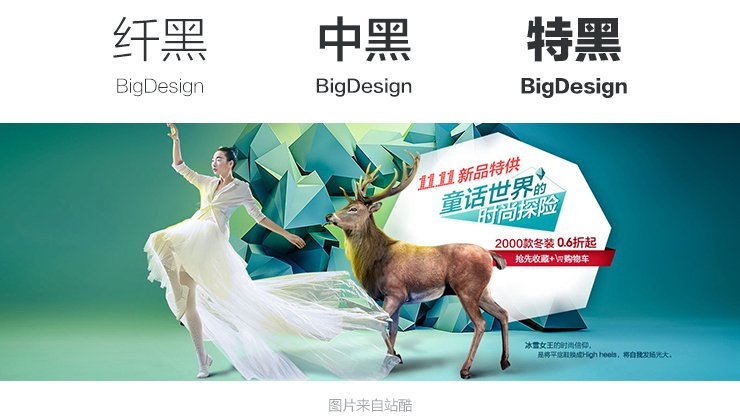
一个banner,一个画册,一个网页,用了一款好的字体都会提升逼格,甚至APP产品本身,如果能够在展示和做设计图的时候采用好的字体,更会为这款产品加分。
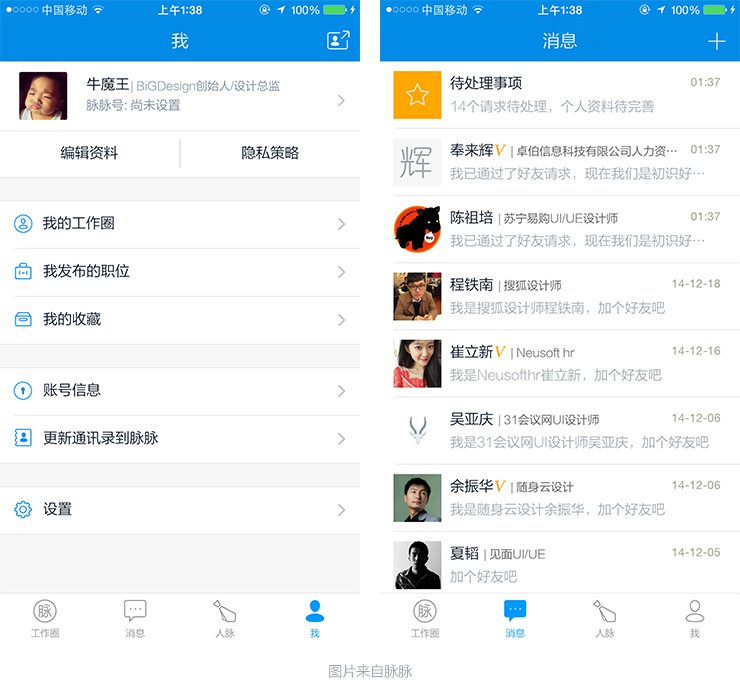
第二款:
这个字体是Adobe与Google宣布推出的一款开源字体,可能不用过多的介绍,相信大部分小伙伴已经下载并且使用了。这款字体更为良心的是,共有七种不同的粗细,无论是做内文还是做标题,绝对足够了。
老牛很喜欢在做PPT以及APP的时候都用到,因为它覆盖率比较广,很多人的电脑都安装并且使用了,其次它七种粗细的天然优势完虐各种PPT文案。
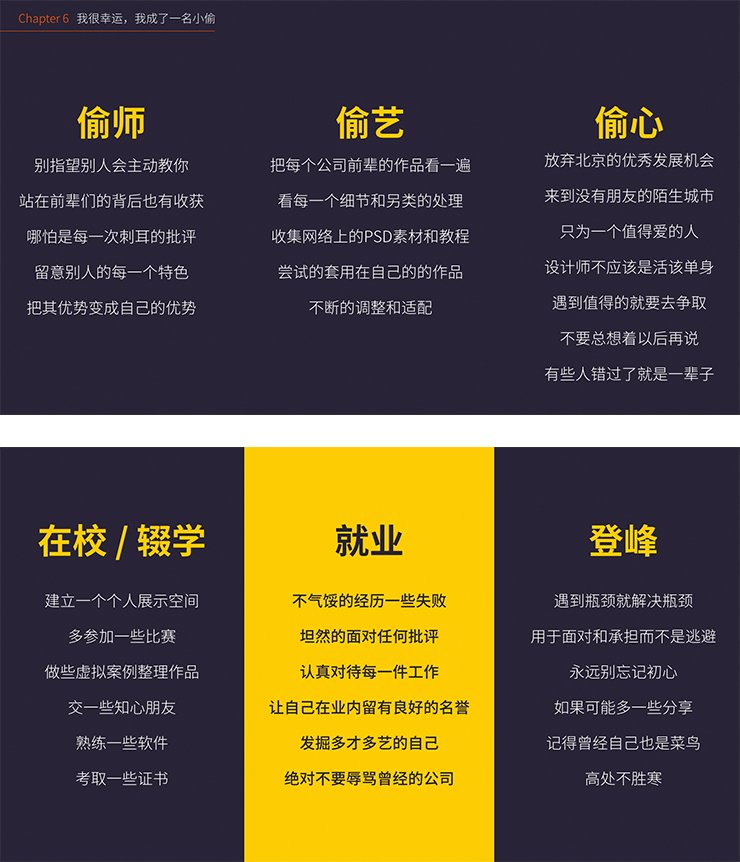
曾经最多使用的是微软雅黑,也是因为其覆盖面比较广,现在有了思源就更多了一种选择。APP的闪屏以及一些Layout图,使用的频率最高。
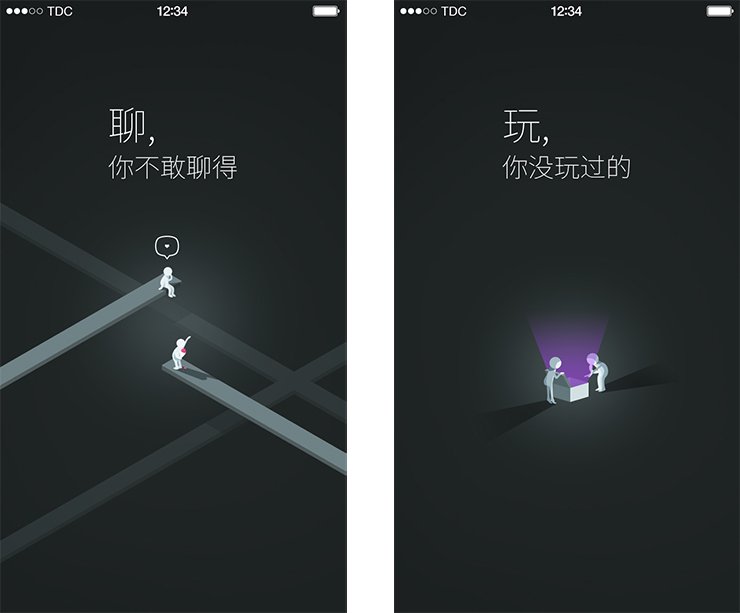
第三款:
这个字体可能每个人的电脑都有(默认字体?),但是使用的人不是很多吧!之前老牛做过的一些设计展示图被很多人问到的字体,就是这个。好吧你让我打出来名字我还真是打不出来的……
它的粗细样式也比较多,共有六种,更主要的是,个人认为它的英文字母会较兰亭和思源更漂亮一些,所以当做中英文结合的时候我就常常使用这套字体。
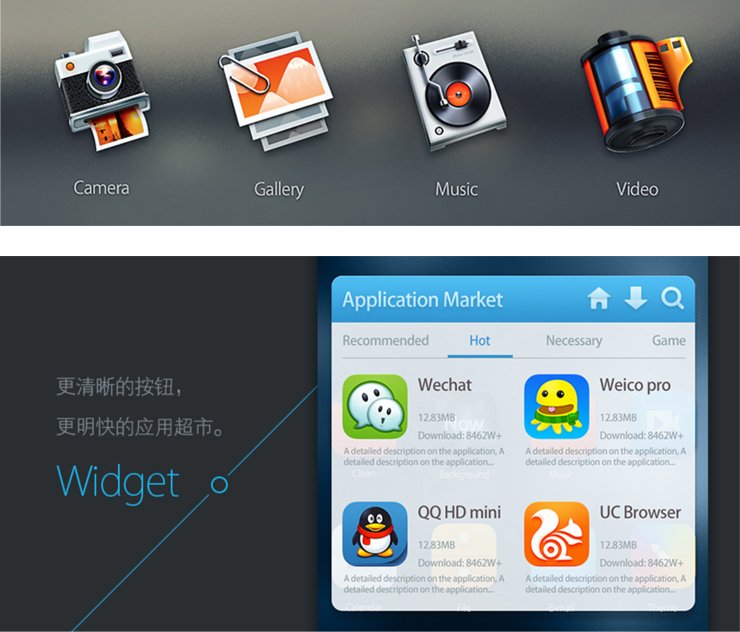
不过它有一个弊端,就是有些情况下某些简体字体它没有,需要转化成繁体才可以用……
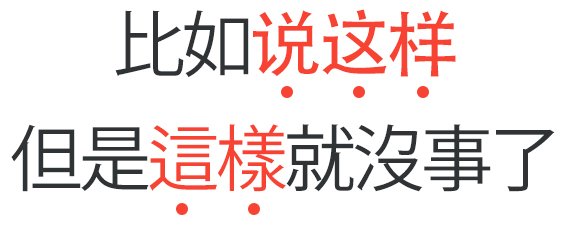
好吧,鉴于你挺好看的,所以就让你任性下去吧,况且用繁体会显得更高逼格一些。如果你不知道怎么打繁体,那么建议可以去搜一下在线“简转繁”,蛮好用的。
实际上还有其他几款日文字体也是相当不错,可以尝试的使用一下。
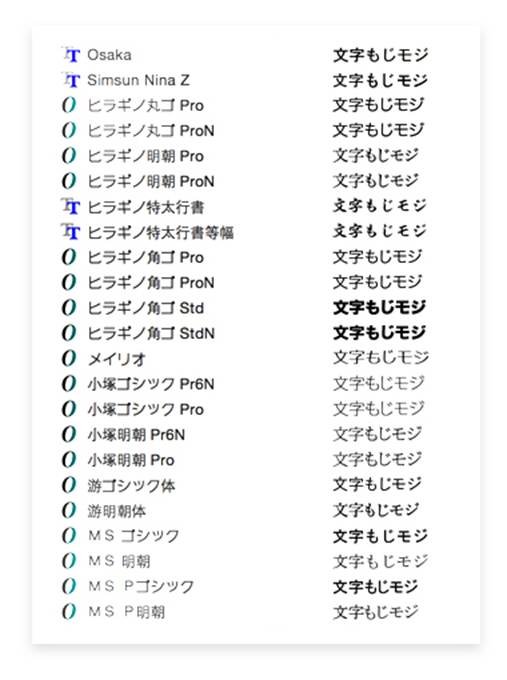
另外的推荐:
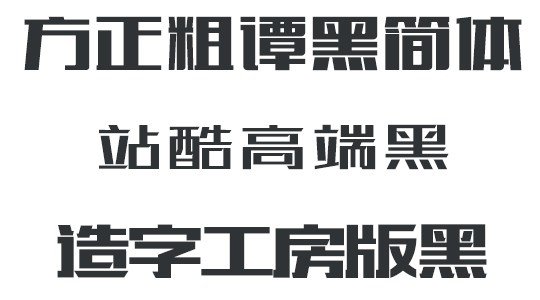
对于比较特异的粗黑体,本人只推荐以上三个。以上三个作为一些特定环境的标题,或者活动banner的文案以及活动页面的大标题,足以,一点简单的倾斜加一点粗边效果,几乎能解决所有需求。
三种字体都是针对于粗体的变形,骨骼硬朗,笔画有力。无论是强力的促销展示还是温柔的示爱活动都可以使用,童叟无欺。
有些毛笔、水墨字体我们没能写的一手好字,能力一般水平有限,怎么办?只好求助于字体。可是说实话,能让人看上眼的毛笔字体还是不多,而且一些狂草、叶根青等等字体本人又不是很喜欢。所以一般我采用这样的方法:
如图,把喜欢的毛笔字体图片保存下来,就可以为我们所用了。而且可以选择透明PNG图层,真是良心品质啊!
处理字体效果的时候,如果能再叠加上一些宣纸、水墨、水彩等素材效果,效果会看起来更好更具有中国范儿!
基本上来说,我们最常用的字体即是这些了,可以看到,本人很少推荐一些特异的字体,因为看起来花枝招展的字体,未必就那么美好,所以,选择最简洁、最规矩的字体,不失为一种最好的选择,剩下的,就交给画面吧!
字体黑名单
既然有推荐,那么必然也有一些不建议使用的。以下字体“黑名单”被老牛列为永远不得出现在设计上以及作品简历上的,它们基本上就是来毁作品的,列举出来供大家引以为戒。
实际上,一个好的字体应该是由设计师亲自设计,但是出于很多设计师并不是从事平面行业,而且即使从事平面行业,字体设计也是非常难的一个环节。以上列举的这些字体,在更多场合和产品中是很中庸的存在,有些甚至非常适合。所以当小伙伴们不知道该选择什么字体,或者电脑里还没有这些,那么建议你开始下载吧。记住,一个画面中禁止超过两种字体以上哈!那样看起来非常杂乱!
其实还有很多很棒的字体,比如造字工房的,时尚中黑简等等,在这里并不一一介绍了,因为本人在平时的设计中就用这几套字体感觉已经足够,更多的是变形和设计效果。
少量的字体大大的提高了自己的工作效率,并且对于我这种强迫纠结选择症的患者来说是一种优选方案,希望对大家也有一些帮助。最后我们看看这些字体的效果吧!